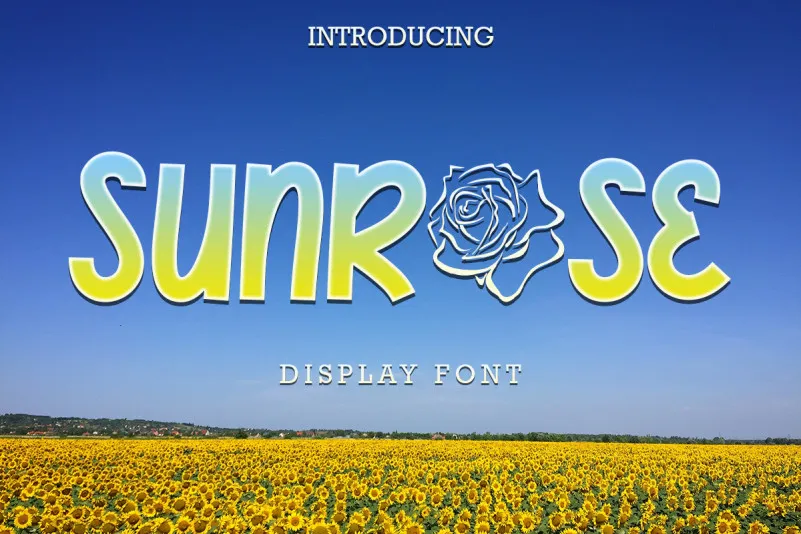
Sunrose Font – Download Grátis
A fonte Sunrose para Display Fonts é uma criação criativa do designer Yoga Letter, ideal para transpor alegria e entusiasmo em seu design. Com linhas finas e um contraste bem equilibrado entre suas letras grandes e espalhadas, ela se destaca como uma opção perfeita para gráficos de marca ou elementos visuais que precisam chamar atenção. O uso desta fonte irá adicionar ao seu design uma sensação vibrante e moderna, capaz de estampar notícias na tela de um tablet ou criar uma assinatura única em um banner impresso. Suas linhas finas e aprimoradas garantem que o conteúdo seja levemente despojado, enquanto suas letras grandes e espalhadas criam um design visualmente interessante. A fonte Sunrose é perfeita para aqueles buscando uma alternativa à tradição que ainda mantém os requisitos de legibilidade. Seja você um designer digital ou um editor gráfico, a Sunrose oferece a oportunidade de criar elementos visuais que não só destacam-se, mas também refletem sua personalidade única. E por apenas instalar e usar essa fonte, você concorda com as Condições Gerais do Produto.